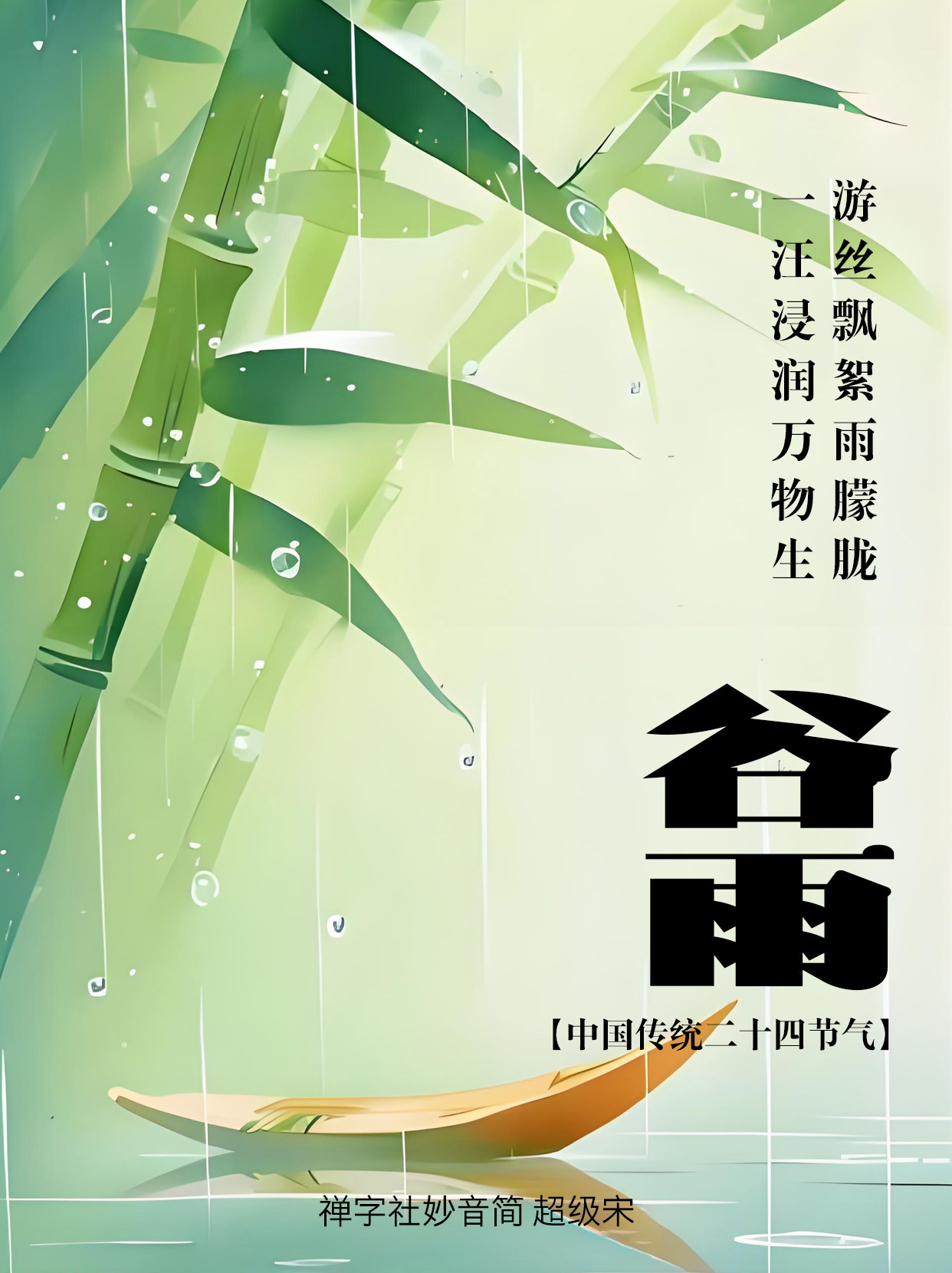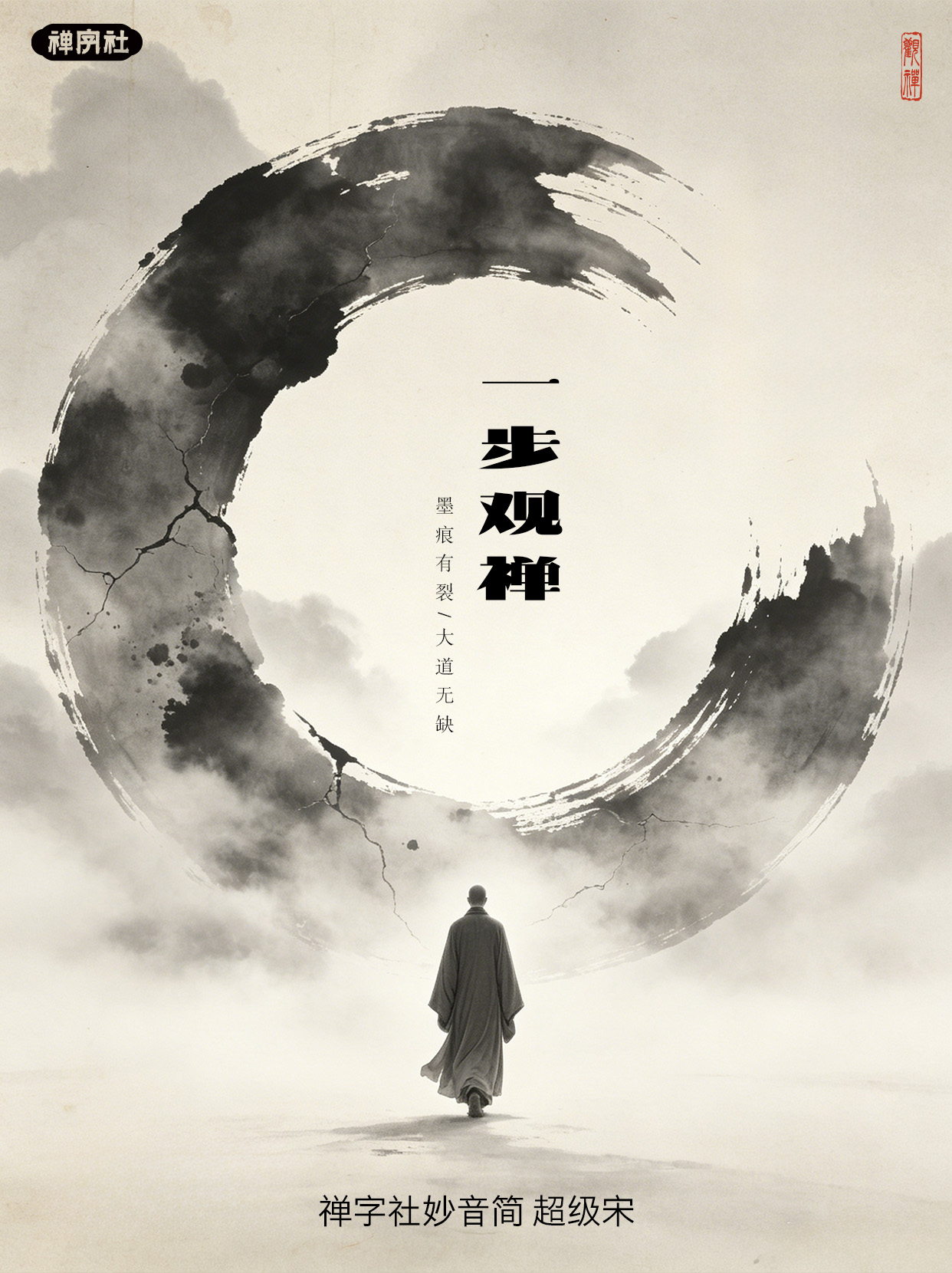
禅字社妙音简 超级宋
禅字社妙音简 超级宋是一款将现代感与复古结构相融合的创意宋体。 字形扁宽粗壮,中宫开阔,给人稳重不迫的第一印象。笔画现代简洁的同时具备圆润复古的风格,将扁半圆形特点融入横画收笔中,横细竖粗的形态对比强烈,折笔处皆做圆角处理,钩笔画的出峰设计汲取了复古的风格并演变成现代化特点的简化处理,整体风格极具辨识度。适用于视频海报、产品包装、广告标题、国潮国风主题场景等。